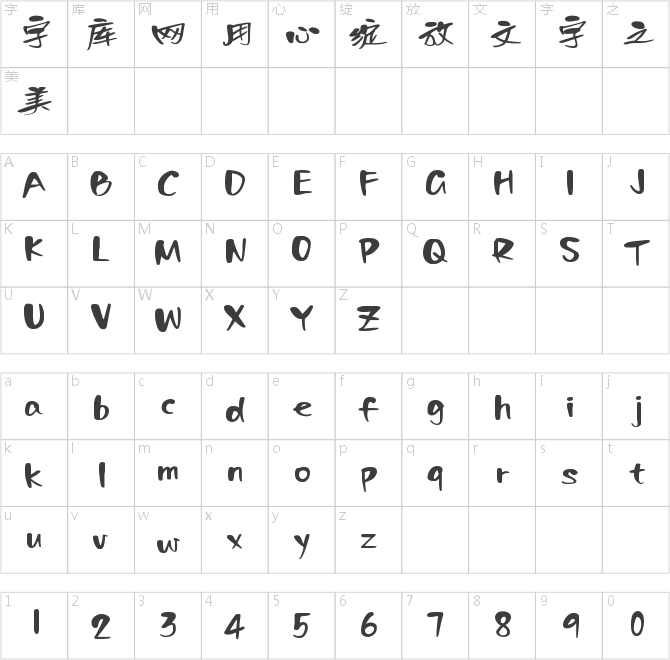
Aa小辣椒 詳情頁(yè)
Aa小辣椒字體下載
Aa小辣椒字體字庫(kù)是一款讓人賞心悅目、百看不厭的中文字體,適合各類廣告和產(chǎn)品包裝設(shè)計(jì)應(yīng)用,字體大小7.65MB,格式為ttf字體,上傳用戶是Aa字庫(kù),作者/版權(quán)方為Aa字庫(kù)